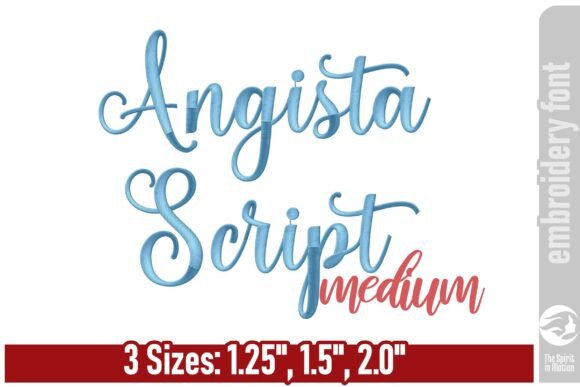
Angista Script Medium Embroidery Font
Пошук відповідних елементів дизайну може бути складним, але Angista Script Medium Embroidery Font пропонує виняткову колекцію, яка миттєво покращить вашу роботу.